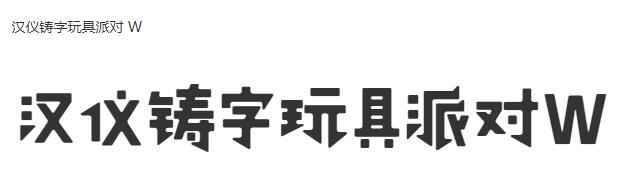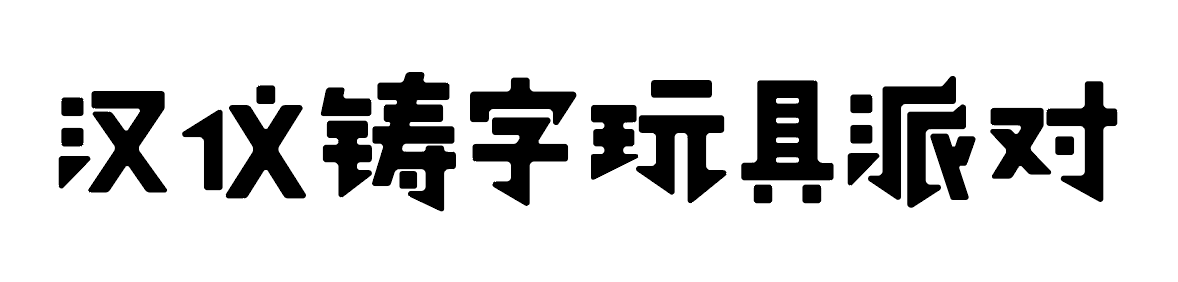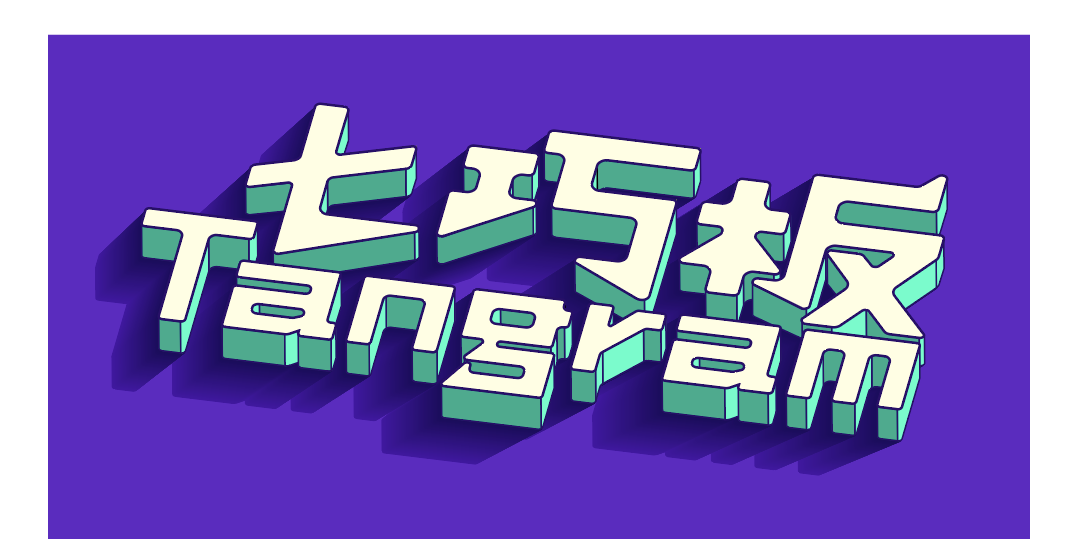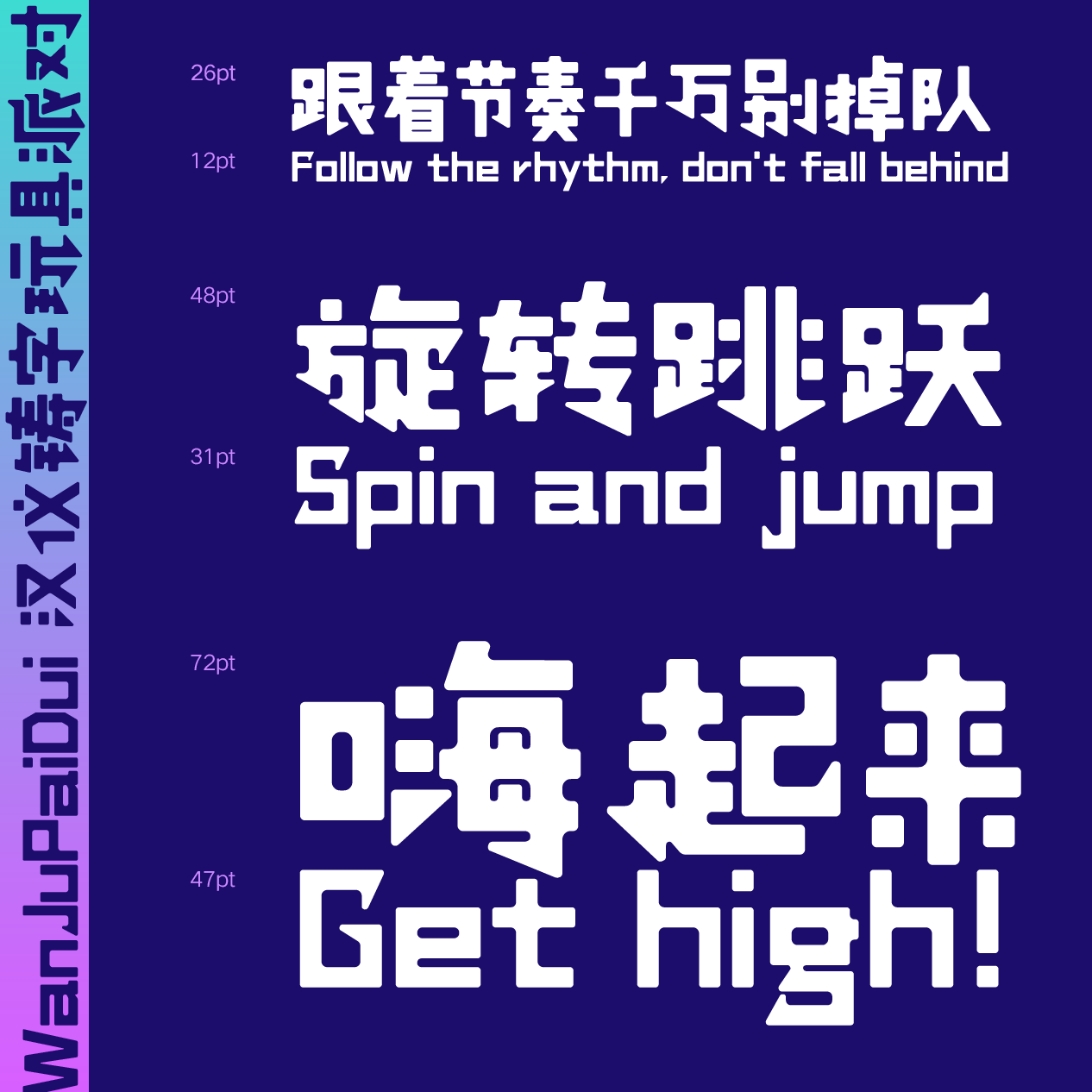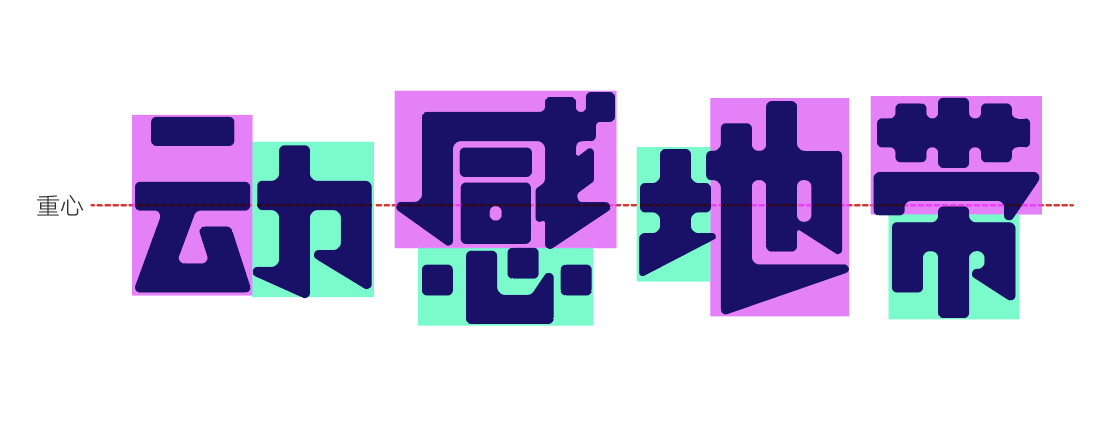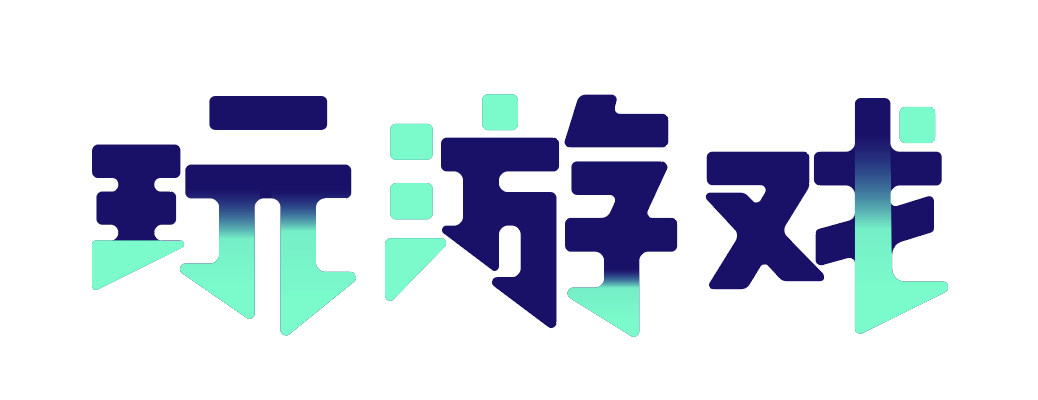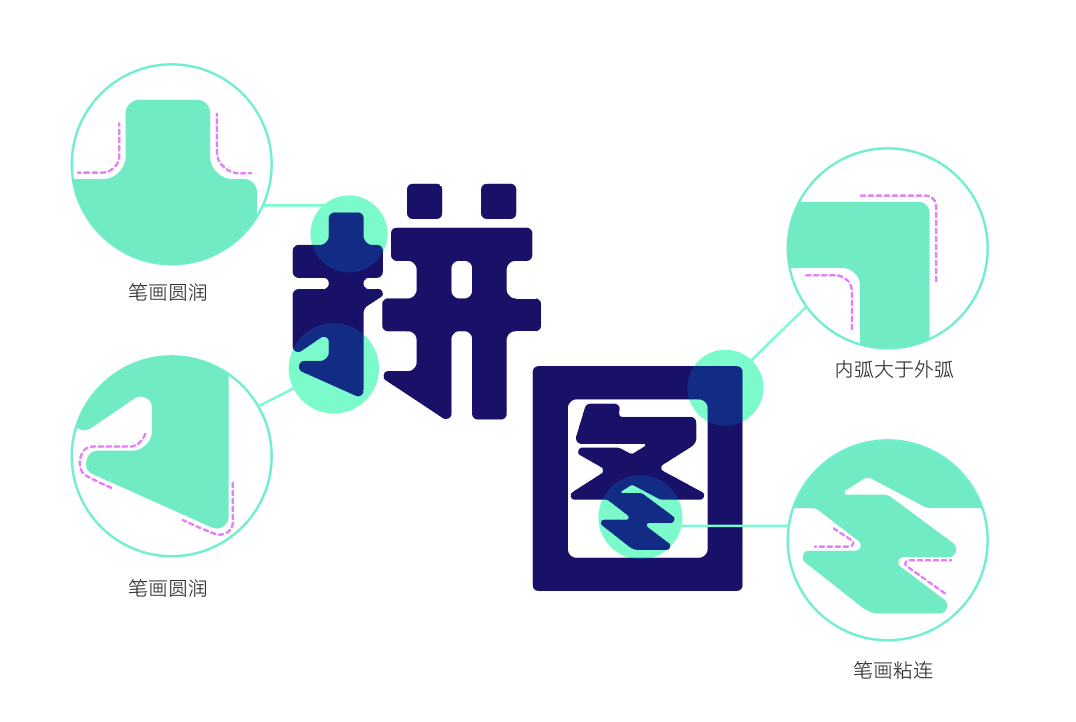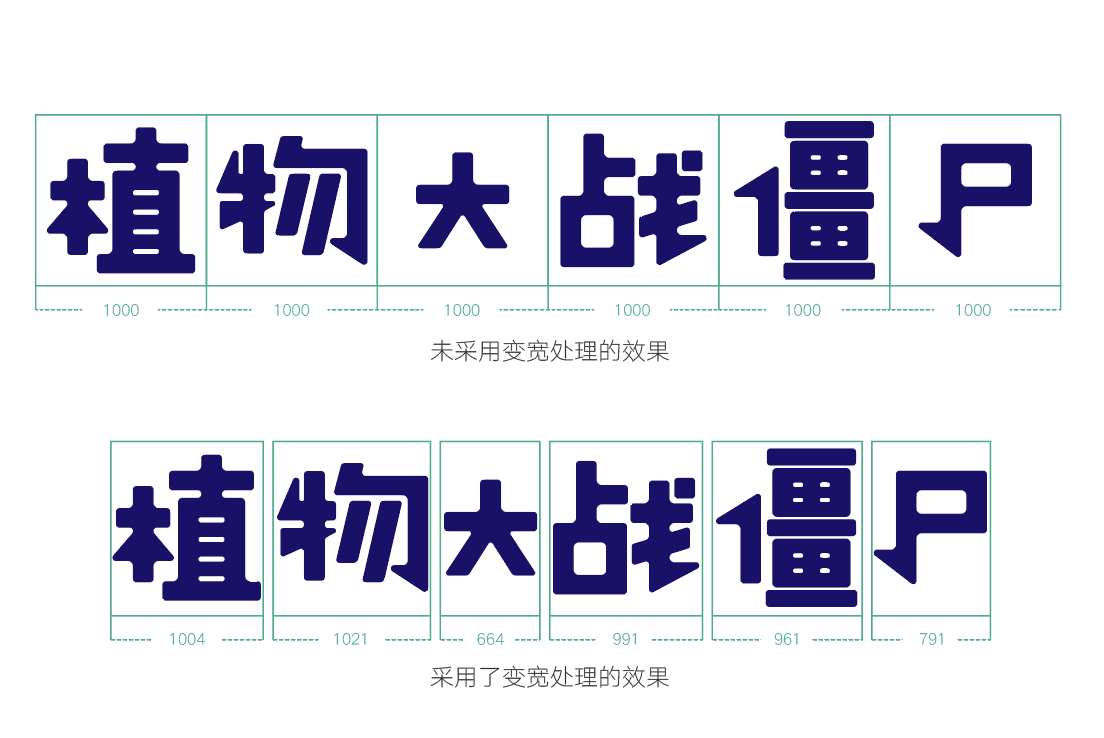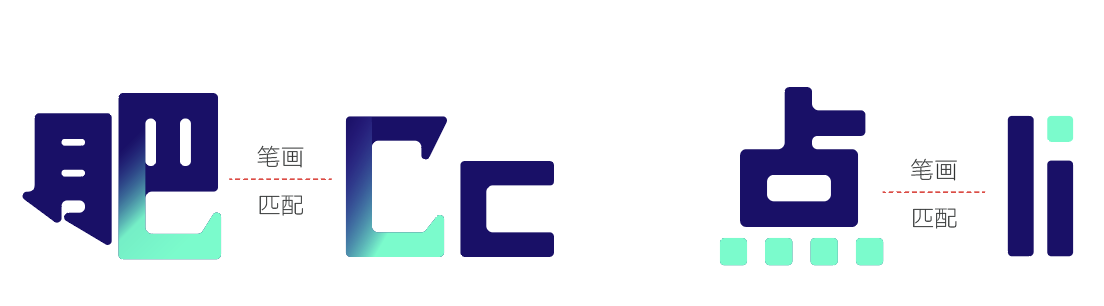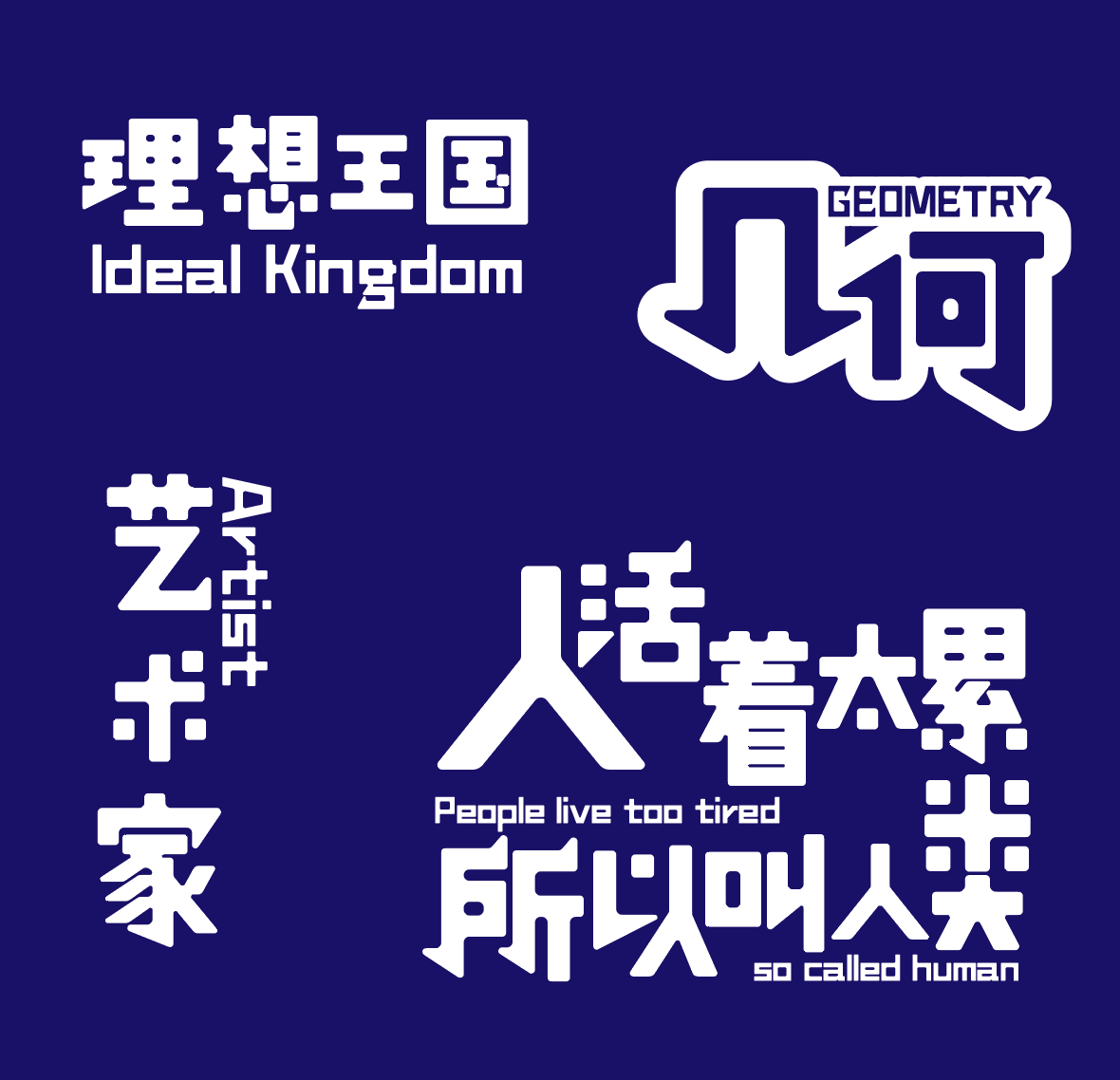
汉仪铸字玩具派对
艺术设计-设计字体
可爱 / 休闲 / 活泼 / 有趣 / 卡通
品牌广告 / 游戏动漫 / 产品包装 / 娱乐综艺 / 书籍封面 / 标志LOGO
汉仪铸字玩具派对 | 可爱积木字体
“汉仪铸字玩具派对”是一款极具趣味性的美术字,它的结构活泼生动,笔画进行了图形化的设计,像七巧板一样拼凑排列,充满着童真与欢乐。适用于少量字数的标题排版设计。
汉仪铸字玩具派对 | 形态多变
“汉仪铸字玩具派对”在保持重心一致的前提下,依据字体结构呈现大小不一的节奏变化,不同笔画间的对比搭配使字体变得更加灵活生动。
汉仪铸字玩具派对 | 笔画具有几何感
“汉仪铸字玩具派对”的笔画就像玩具积木一样。点笔画运用圆润的正方形,提笔和勾笔运用圆润的三角形,卡通效果十足。
“汉仪铸字玩具派对”的笔画间有一种粘连感,线条边缘曲线细腻。这种藕断丝连般圆润的处理方式弱化了字体的锋利感。
汉仪铸字玩具派对 | 变宽字体
由于“汉仪铸字玩具派对”不同文字的字面差异较大,考虑到排版使用上的体验感,我们在技术上采用了字体变宽的处理方式,使字体的排版效果更加舒适自然。
汉仪铸字玩具派对 | 中西文匹配
“汉仪铸字玩具派对”的西文字母充分吸收了中文童真、欢快的风格特点,有着相同的笔画特征,中西文搭配使用十分和谐。
汉仪铸字玩具派对 | 排版效果